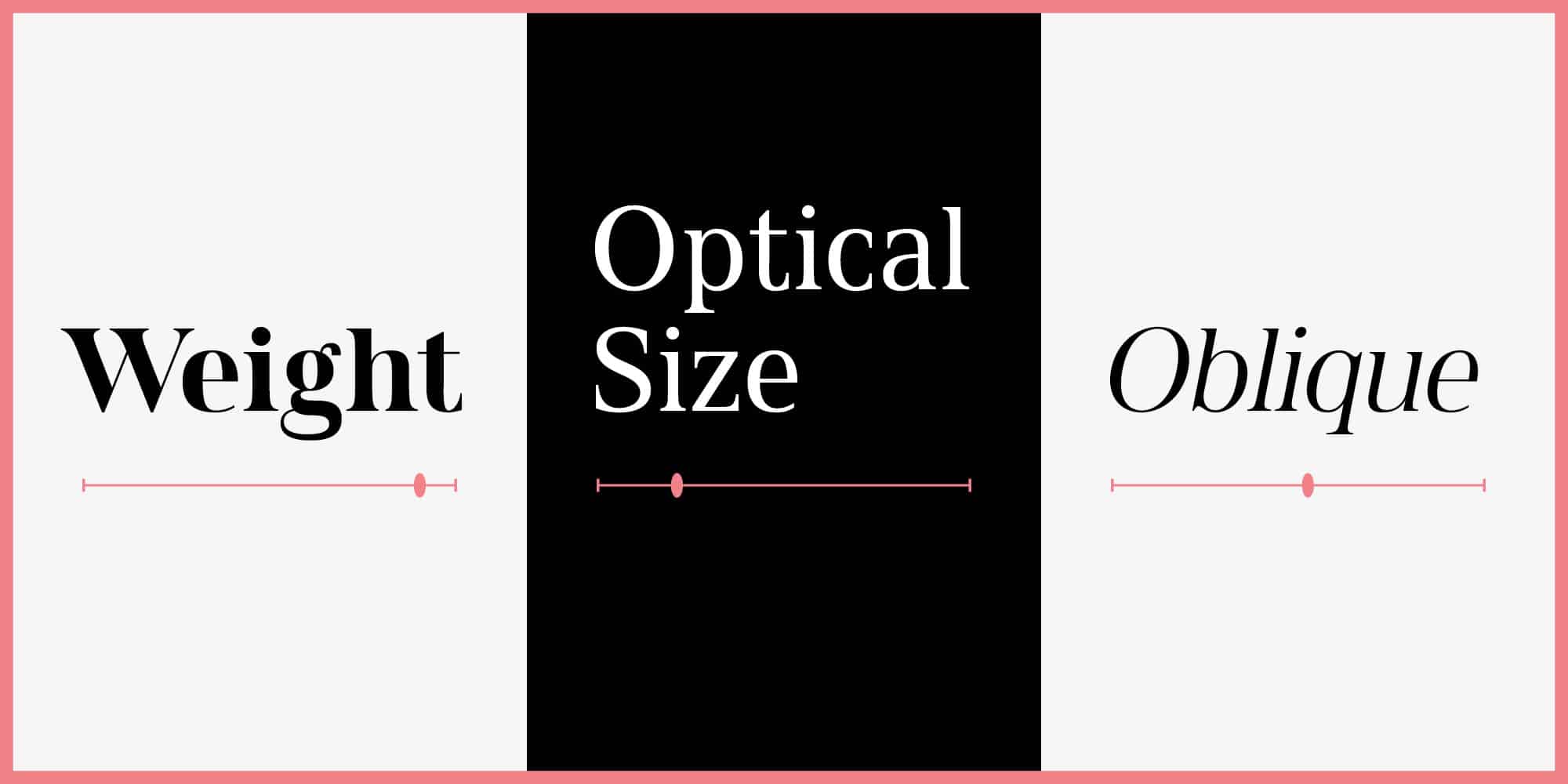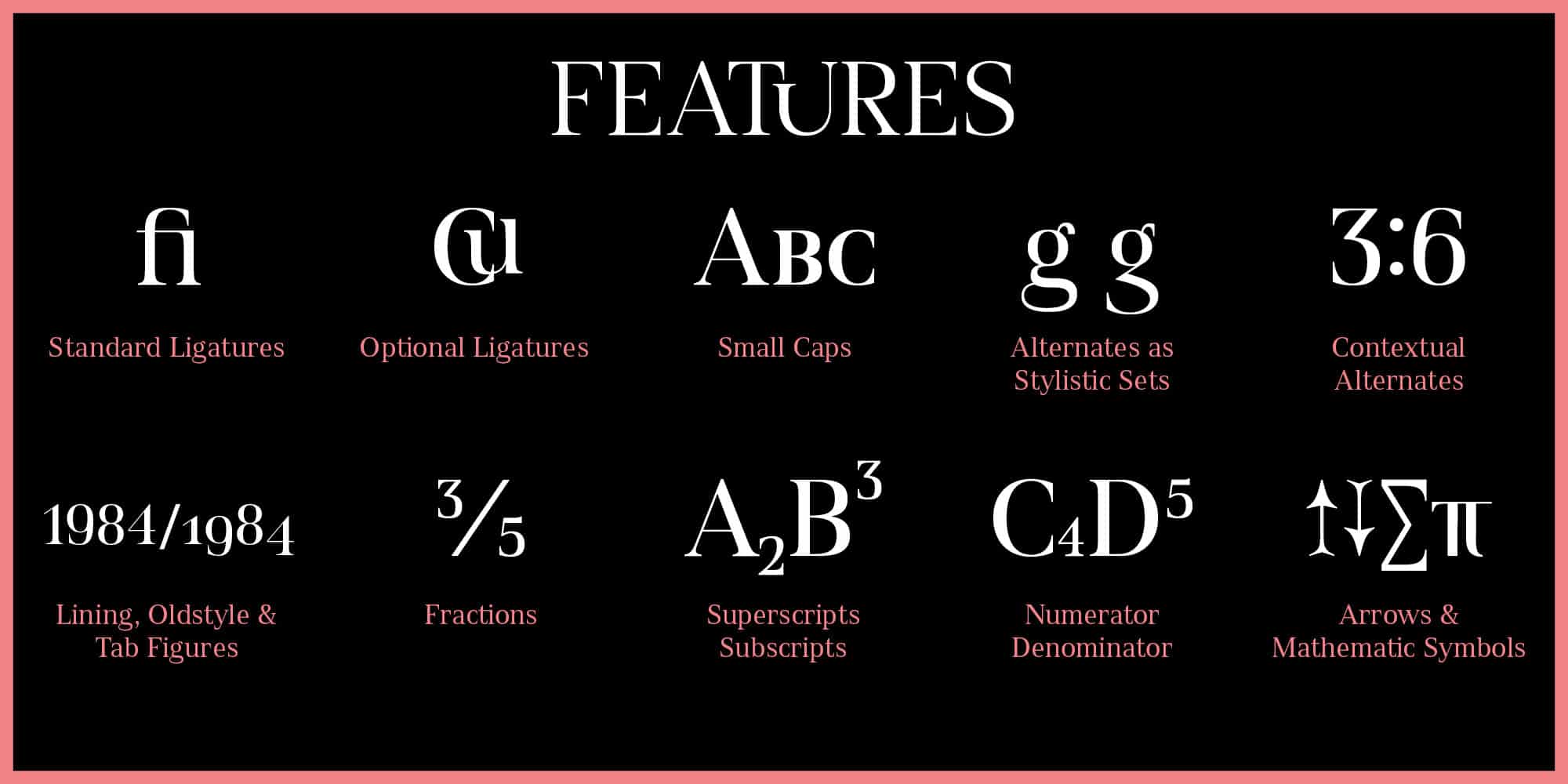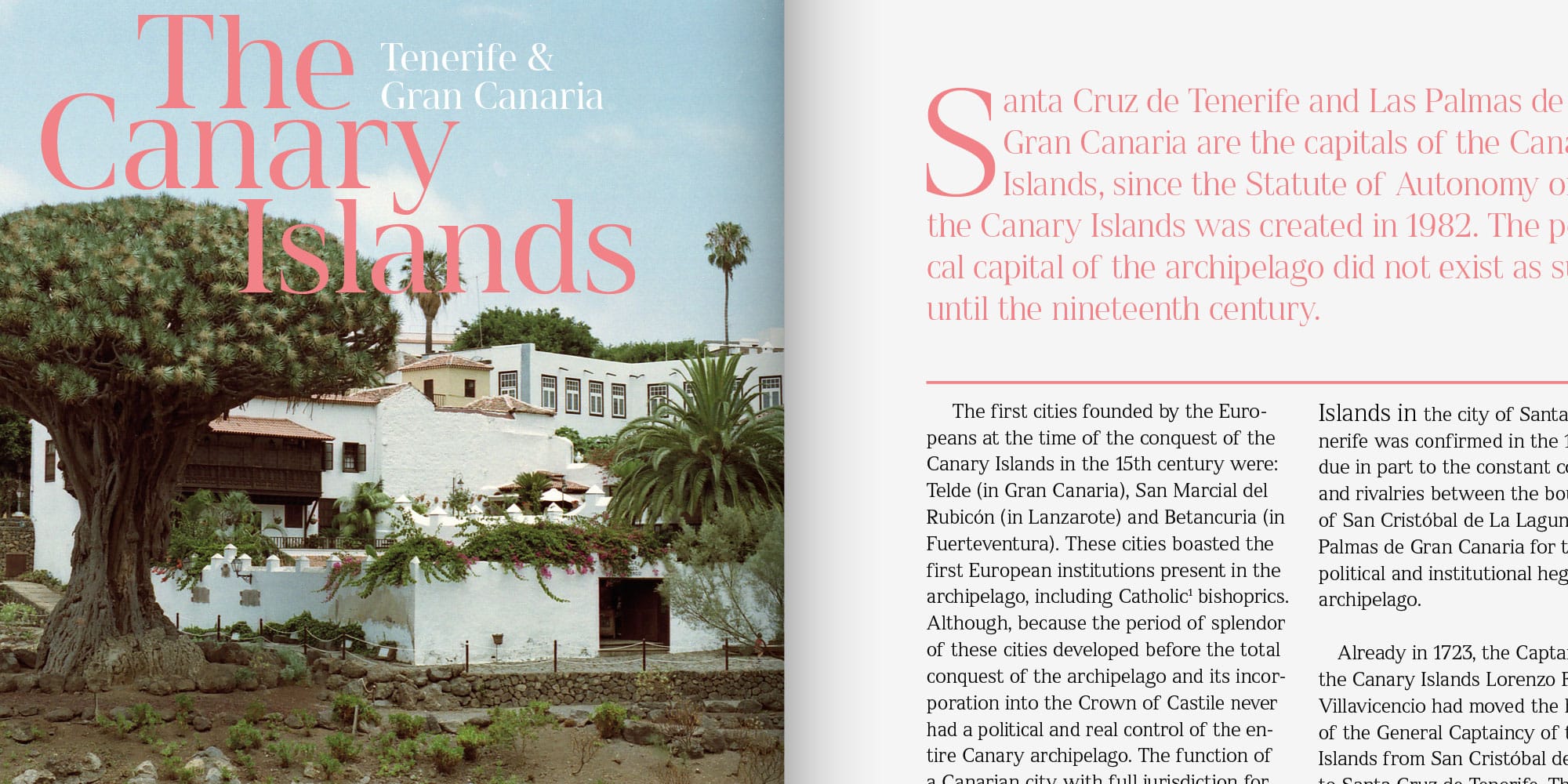
Bereits vor etwa anderthalb Jahren veröffentlichte Julien Fincker die Spitzkant Schriftfamilie – in zwei optischen Größen, für Headlines und Text. Nun ist die umfangreiche Schriftfamilie auch als Variable Font veröffentlicht worden. Variable FontsEine Variable Font ist eine Schriftdatei, die mehrere Schriftschnitte, etwa von dünn bis fett oder von schmal bis breit, nicht als separate Einzeldateien enthält, sondern als ein einziges, stufenlos veränderbares System. Statt zwischen fest definierten Schnitten wie Regular, Bold oder Condensed zu wählen, lässt sich bei einer Variable Font jeder Zwischenwert entlang definierter Achsen frei einstellen. Technisch basiert das Format…
Weiterlesen: Variable Fonts vereinen nahezu unendlich viele Schriftschnitte in einer einzigen Schriftdatei. Über drei Regler für Gewicht, Kursive und optische Größe kann somit der gewünschte Schnitt ausgewählt werden. Diese Font-Technologie eignet sich daher hervorragend für die typographische Gestaltung von responsiven Screen-Cases. Besonders Web-Developer erfreuen Variable Fonts, da diese eine deutlich kleinere Datenmenge einnehmen als übliche Web-Fonts. Doch auch für spannende Typo-Animationen eignen sich Variable Fonts hervorragend. Auch für das klassische Layouten eignen sich Variable Fonts. Je nach Einsatzgebiet wünscht man sich zum Beispiel gerne mal etwas zwischen einem Light- und einem Regular-Schnitt. Dieses Problem lässt sich nun Dank der Regler ganz einfach beheben.
Spitzkant ist eine Serifen Schriftfamilie, die sich durch starke Kontraste charakterisiert. Spitze, scharfkantige Serifen und Kanten stehen runden und feinen Formen gegenüber, was sie sehr individuell und ausdrucksstark erscheinen lässt. Dadurch ist sie insbesondere für Branding, Editorial, Packaging und Werbung geeignet. Der kontrastreichen Display-Variante wurde eine kontrastärmere Text-Variante beigestellt, so dass Spitzkant in Kombination sowohl für starke Headlines als auch für umfangreiche Fließtexte geeignet ist. Ein Allrounder, der für viele Zwecke einsetzbar ist.
Mit über 850 Zeichen deckt sie über 200 lateinbasierte Sprachen ab. Sie verfügt dabei über eine Vielzahl an Währungszeichen und einer ganzen Reihe Open Type Features, die auch alle im Variable Font verfügbar sind. Es gibt zum Beispiel alternative Zeichen als Stylistic Sets, Small Caps, automatische Brüche und viele weitere Features.
Im Besonderen sei hier die umfangreiche Auswahl an Ligaturen (Standard und Optional) hervorgehoben. Mit über 95 verschiedenen Ligaturen bieten sich viele Möglichkeiten, Headlines und Logos eine individuelle Note zu geben.
Julien Fincker lebt und arbeitet bei Stuttgart. Nach dem Studium zum Dipl. Kommunikations- und Grafikdesigner machte er Station bei prägenden Agenturen und Unternehmen, wie dem Grafischen Atelier Stankowski + Duschek. Heute arbeitet er als Art Director bei campra – Büro für Kommunikation. Auch Frei- und Nebenberuflich legt er großen Wert auf multidisziplinäres Schaffen – insbesondere auf Typedesign.